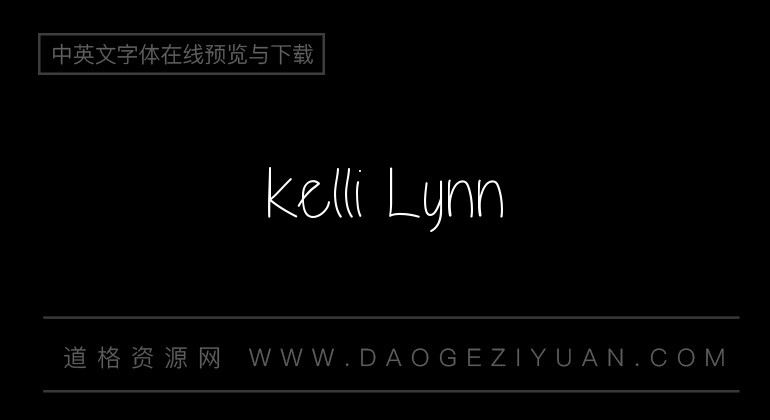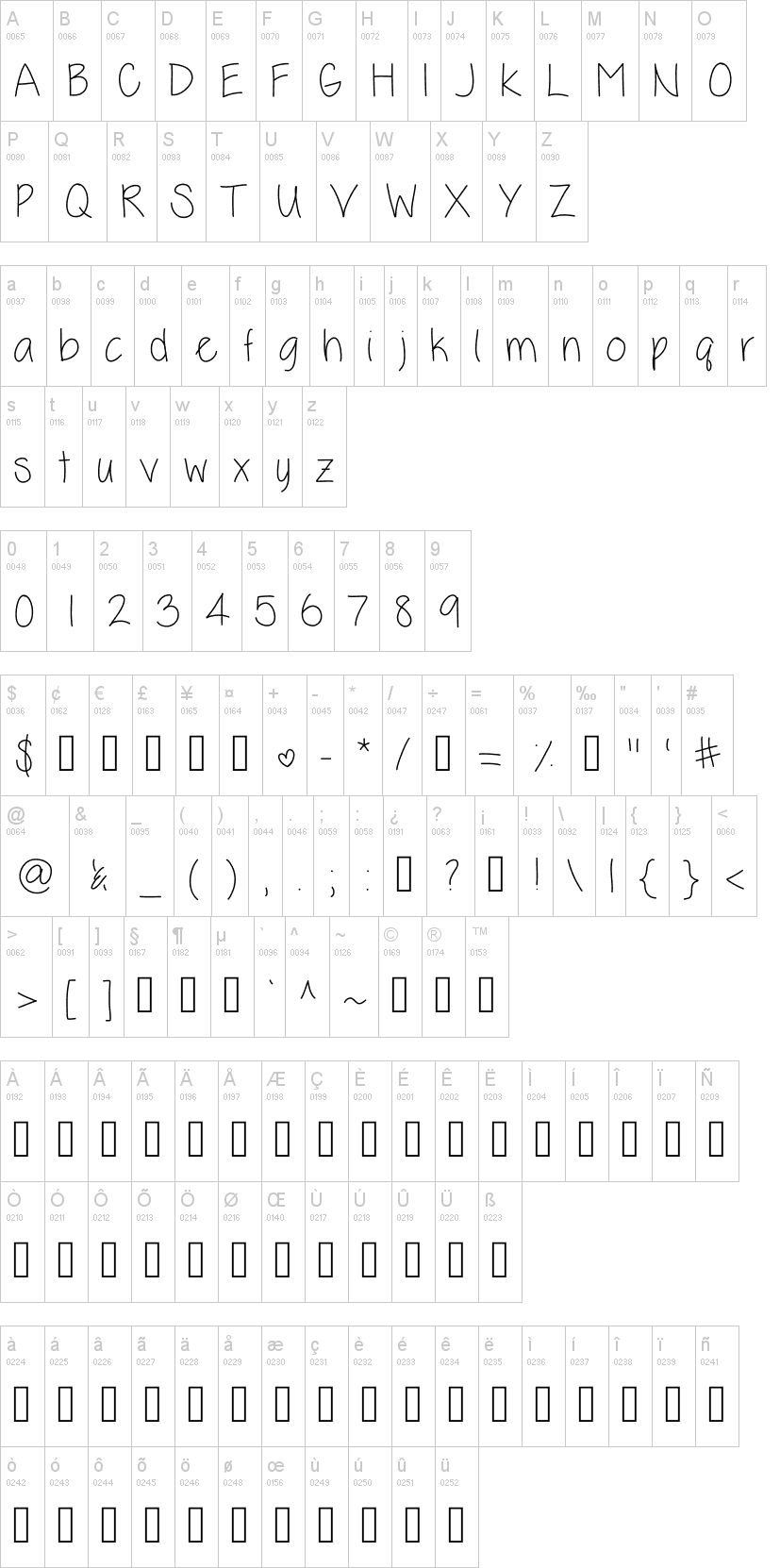
Kelli Lynn
Kelli Lynn 字体是一款脚本字体,由英国设计师Kelli Lynn 创作。这款字体拥有优雅的笔画,温柔的线条,流畅的曲线,给人一种温柔的感觉。Kelli Lynn 字体可以用于多种不同的应用,如海报、书籍、网页、卡片等。它可以为设计师提供无限的创意空间,可以让您的设计更加精致和有趣。
Kelli Lynn是一款非常不错的手写艺术字体,具有很好的视觉感,适合于文化类的宣传设计、商业类品牌的广告和产品包装设计以及个性化文字排版等较多场景。